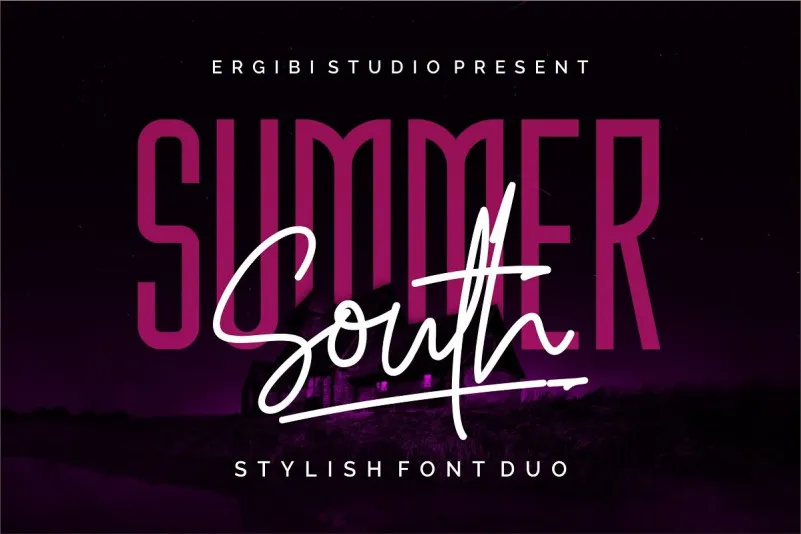
Summer South Font Duo – Fonte Grátis
Summer South Font Duo
A Summer South Font Duo é uma combinação poderosa de duas fuentes sem serif que vai revolucionar seu design digital. Esta opção gratuita inclui uma elegante fóntica script e um belo tipo aberto, já combinados e prontos para serem usados juntos no próximo projeto! Ela se destaca como uma dupla ultra esparsa, oferecendo um estilo romântico e retro que é perfeito para destacar qualquer design. Ideal tanto para designers profissionais quanto iniciantes, esta fonte é a escolha certa para aqueles procurando por novas maneiras de expressar sua identidade visual no mundo digital.